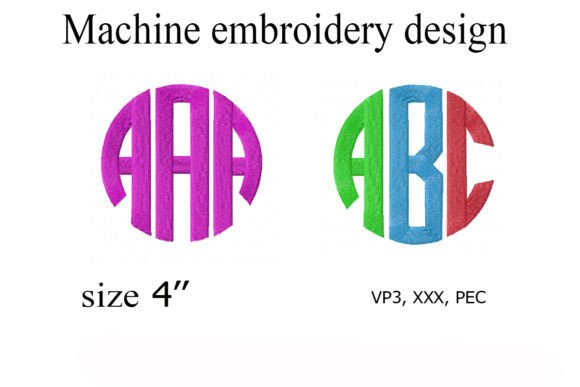
Circle Monogram
Circle Monogramのような高品質の素材をお探しの場合、このプレミアムパッケージはクリエイティブなプロジェクトに素晴らしい選択です。
POD(オンデマンド印刷)製品、結婚式の招待状、またはソーシャルメディアのグラフィックを作成している場合でも、Circle Monogramは理想的です。